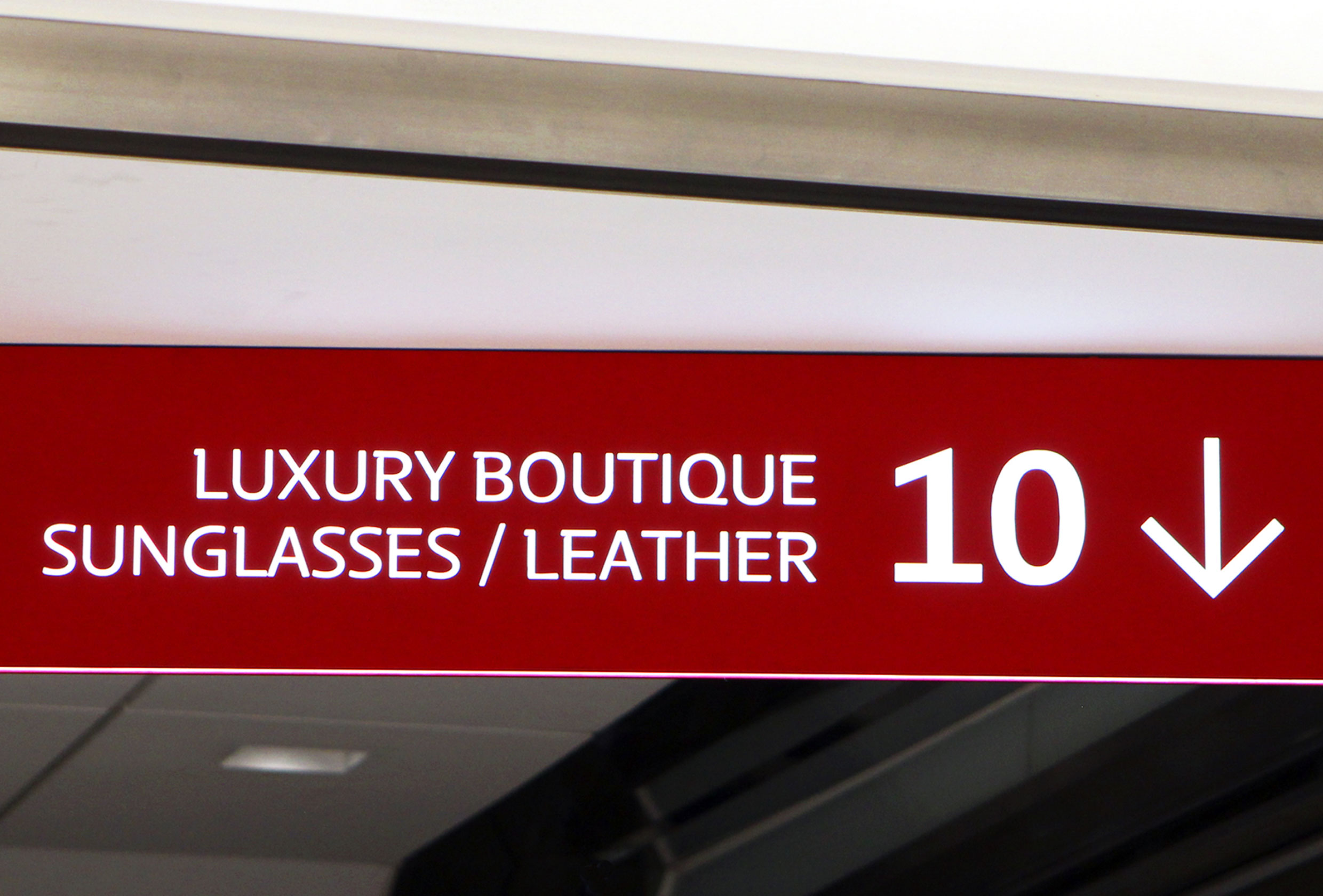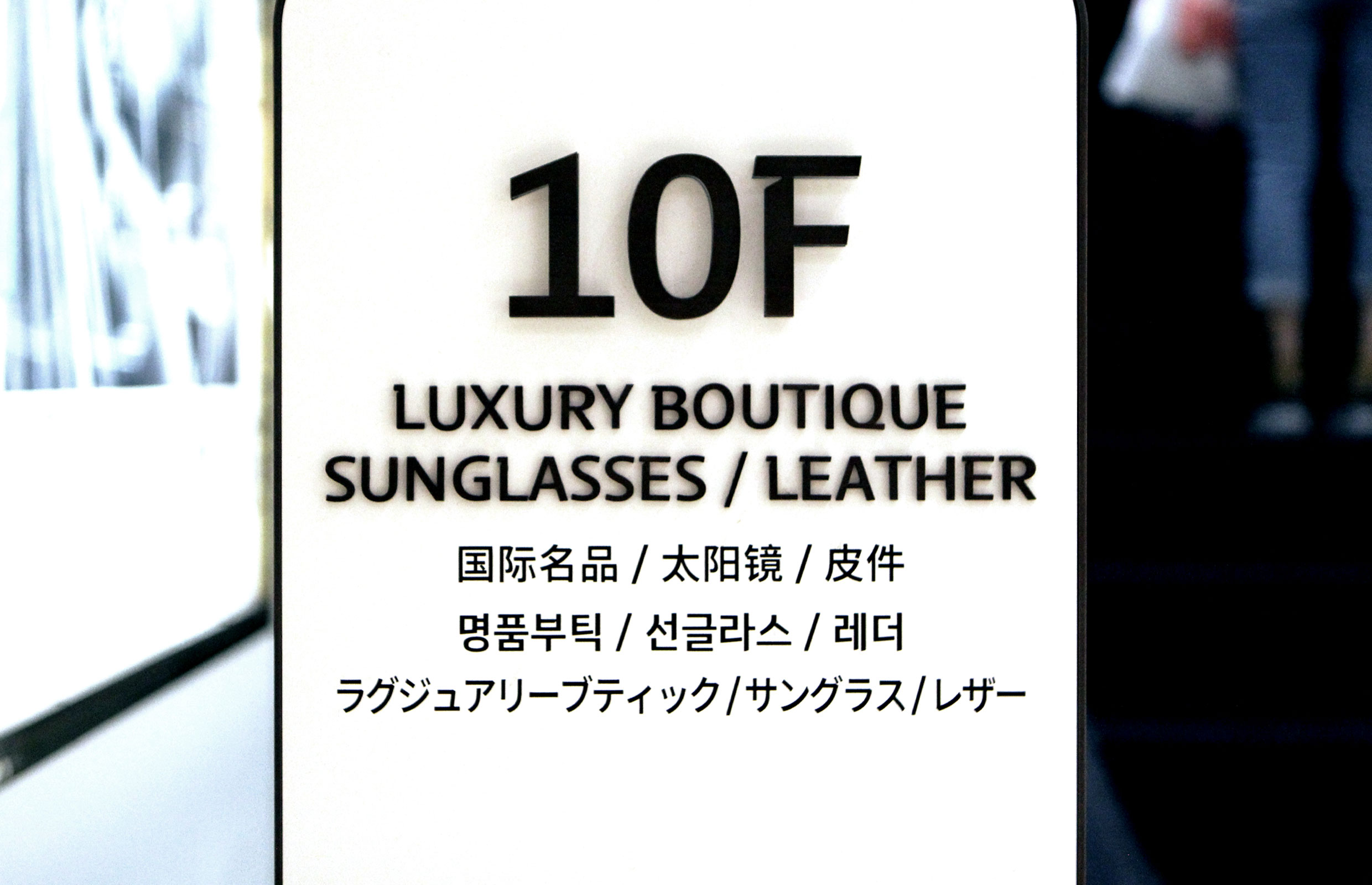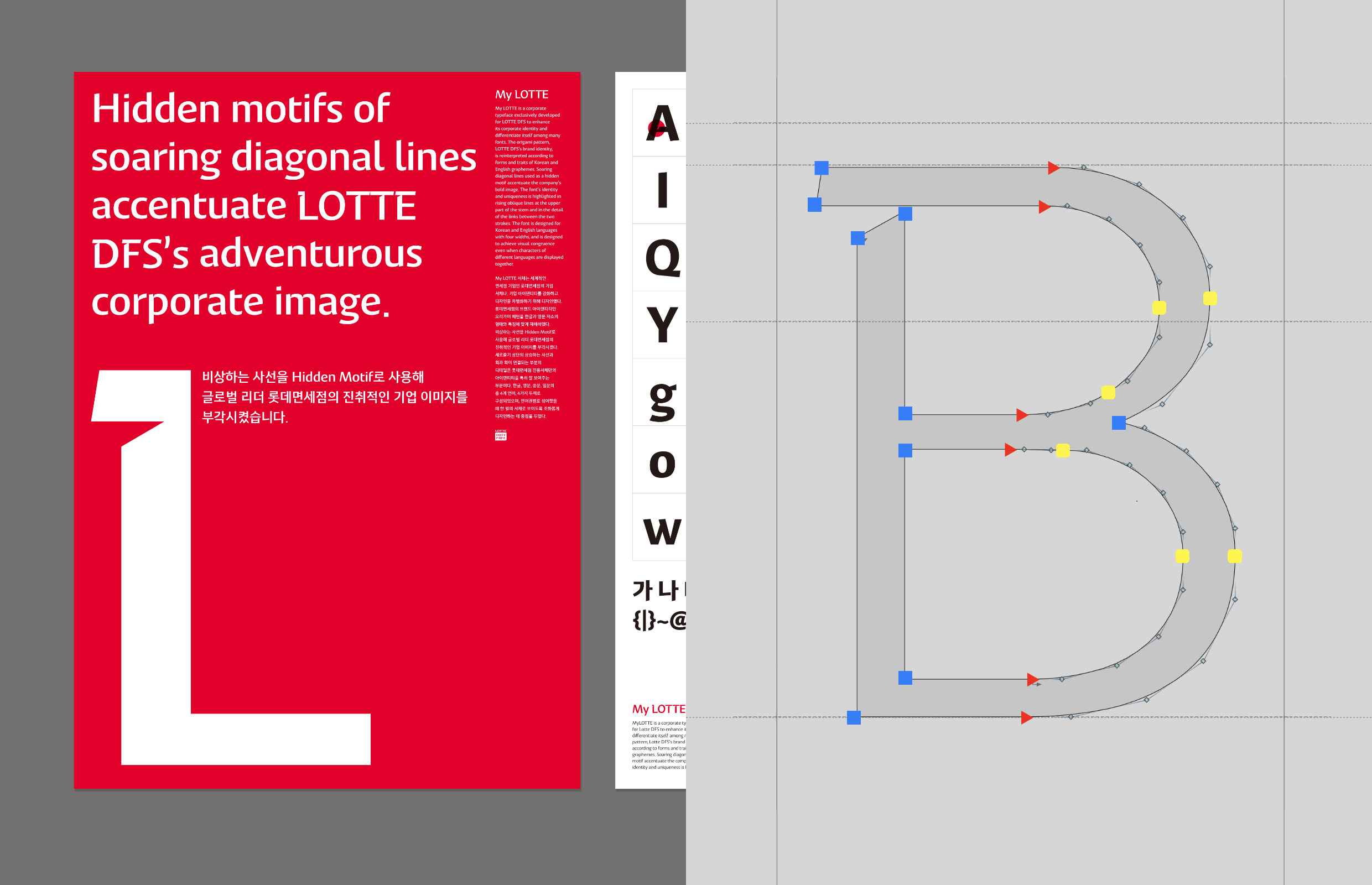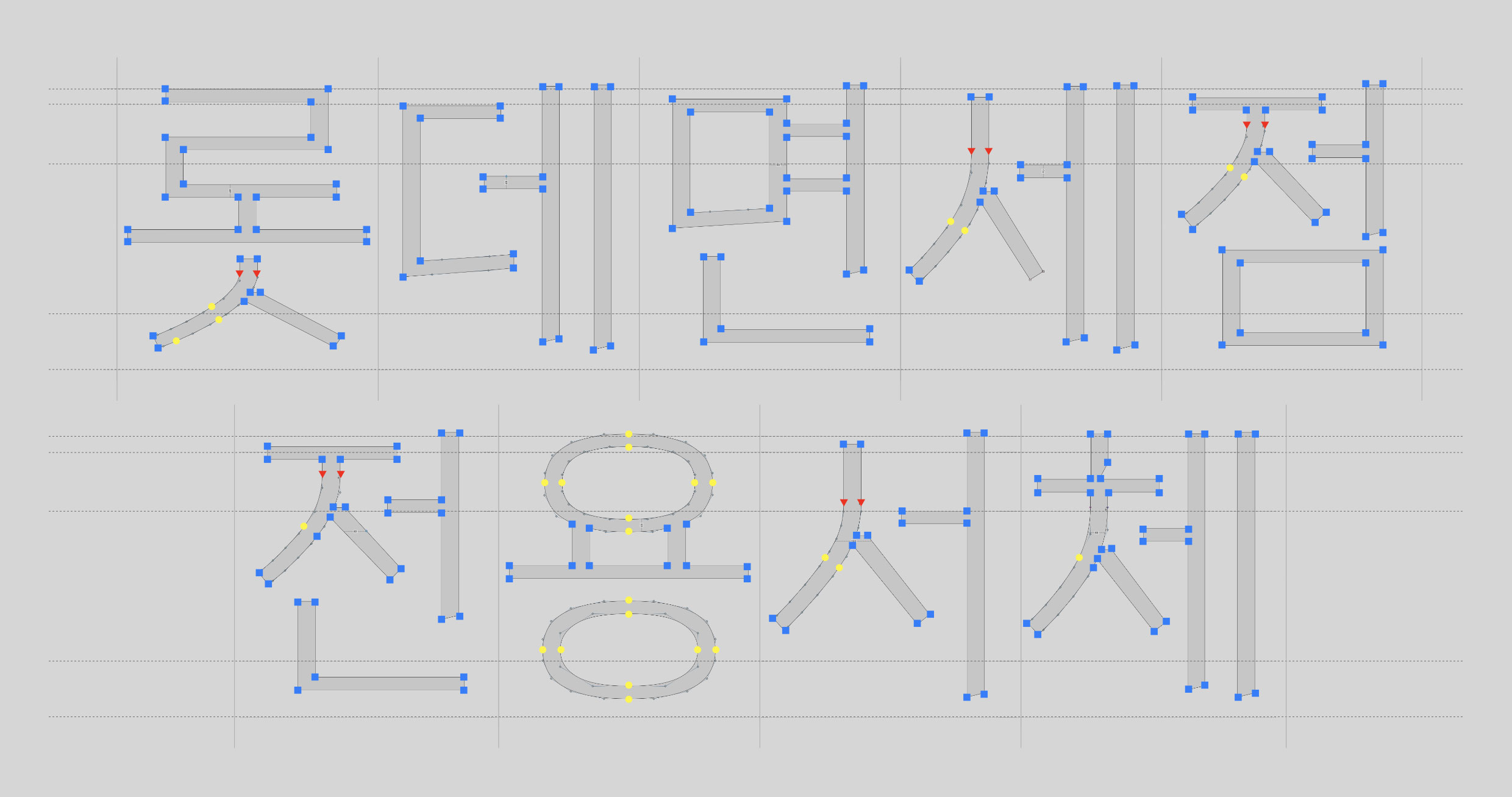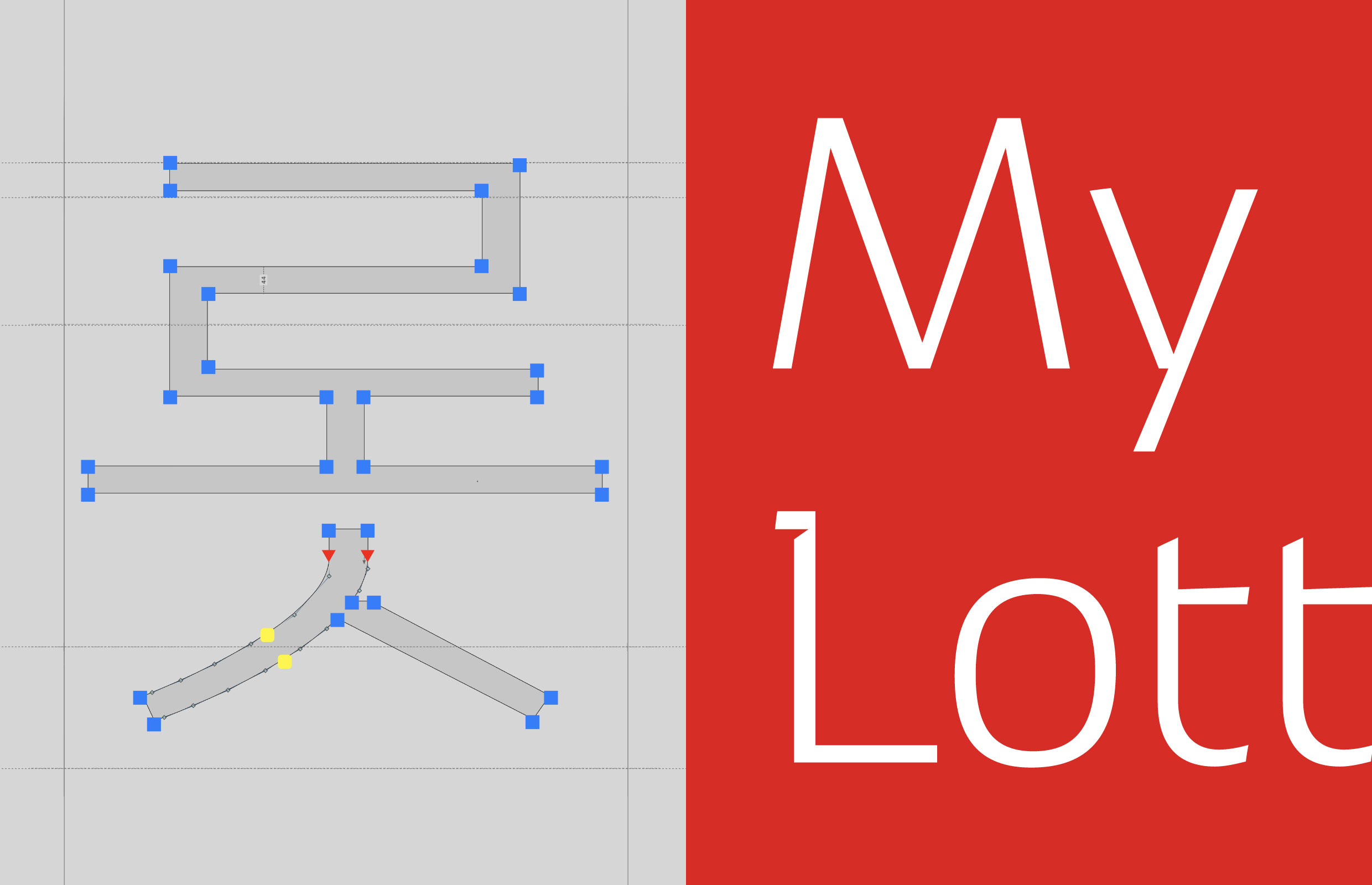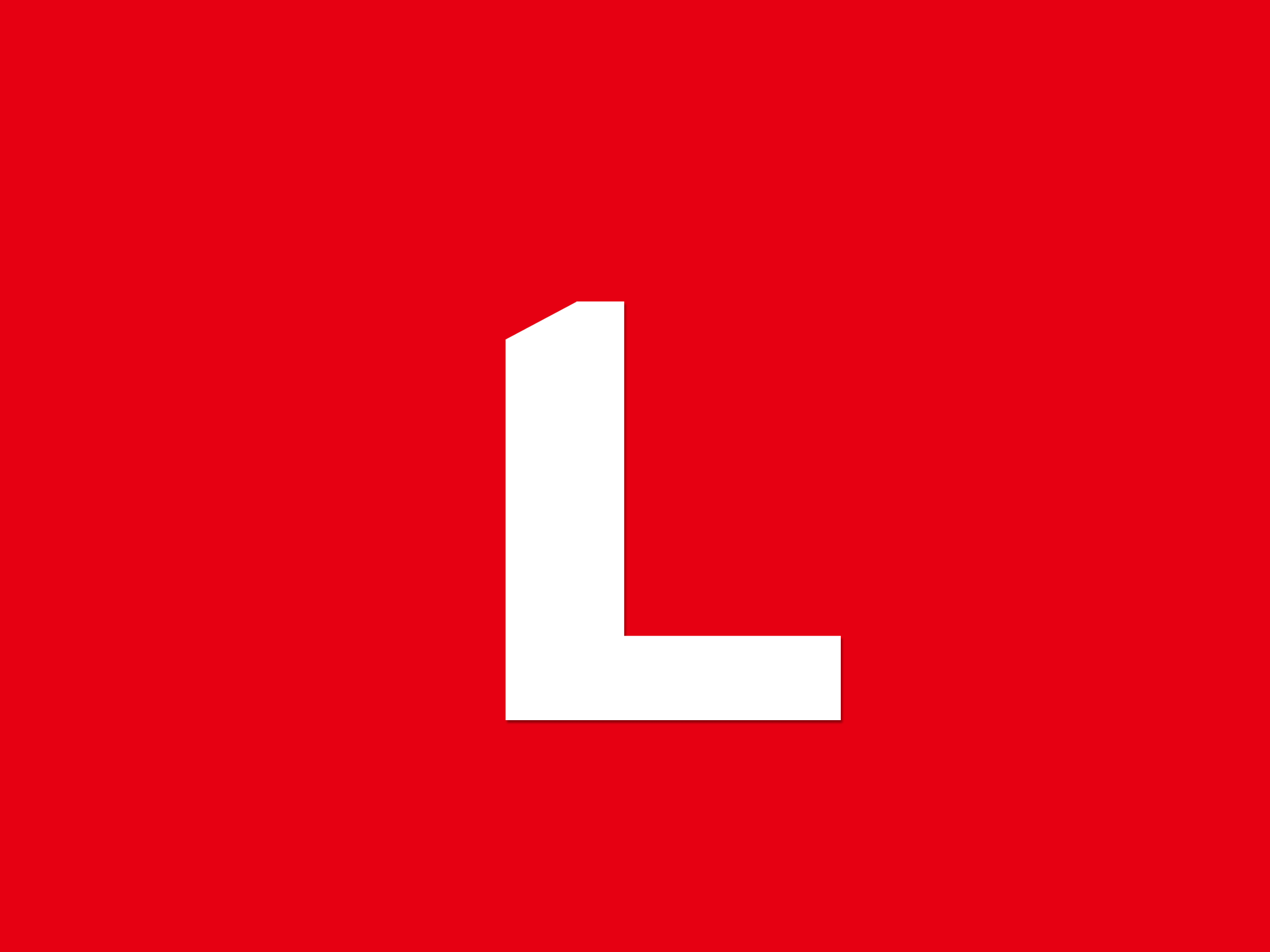
롯데면세점 [MyLOTTE]
비상하는 사선과 롯데면세점의 VI(Visual Identity)인 오리가미 패턴을 Hidden Arrow로 재해석하여, 업계를 선도하는 Global Leader의 이미지를 표현했다. Red Dot Design Award 2017 커뮤니케이션 부분, 타이포그래피 분야 Best of Best 수상과 IF 디자인 어워드 2018 커뮤니케이션 부분 본상을 수상했다.